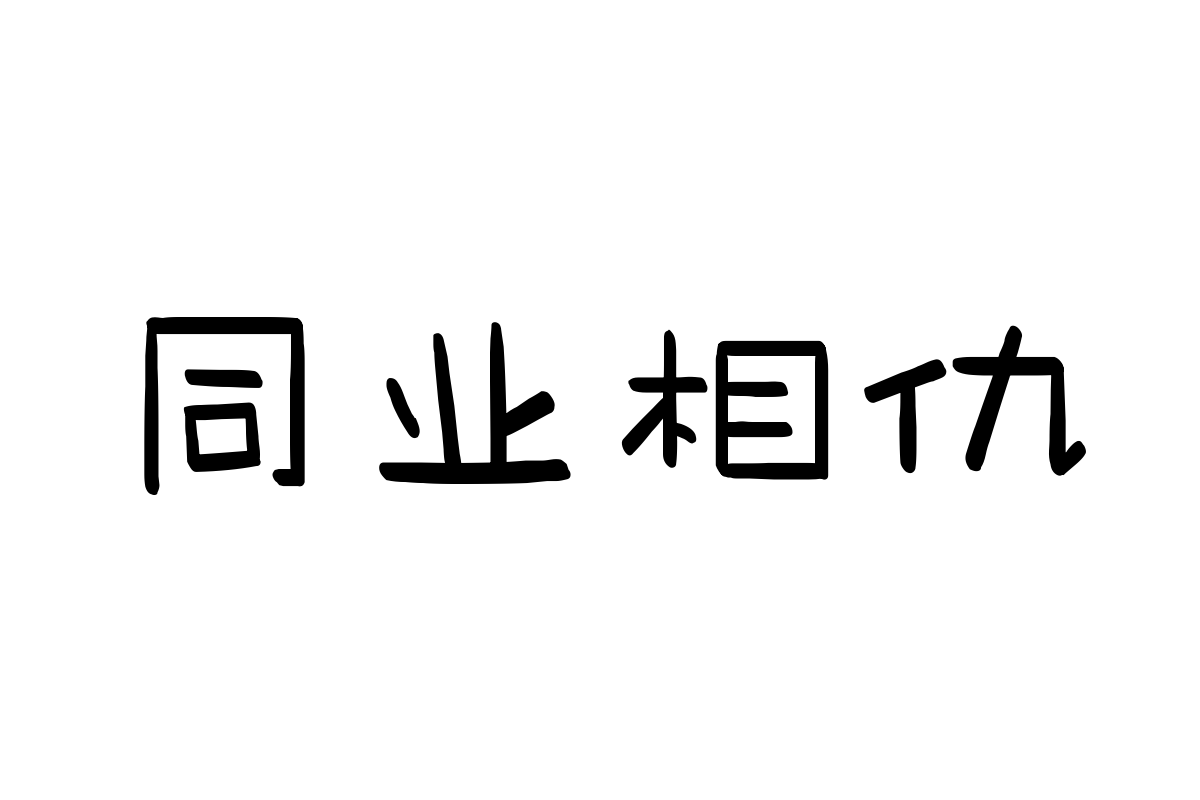
文道小鸡体是一种中文字体,由设计师文道创作。这种字体具有独特的艺术风格和视觉效果,给人以活泼、可爱的感觉。它的特点是笔画圆润、流畅,字形紧凑而富有变化,给人一种轻松愉快的阅读体验。
文道小鸡体适用于各种场合的文本设计,如广告、宣传册、报纸、杂志等。它的应用范围非常广泛,可以满足不同设计师的需求。无论是用于商业广告还是个人作品,文道小鸡体都能展现出其独特的魅力。